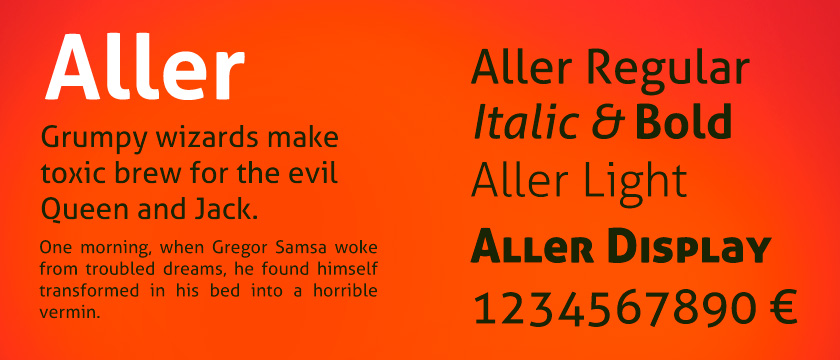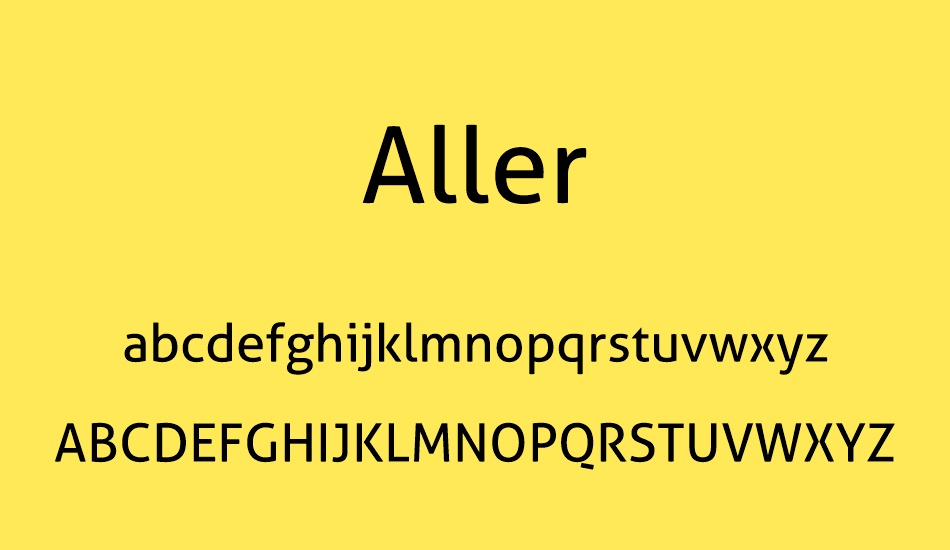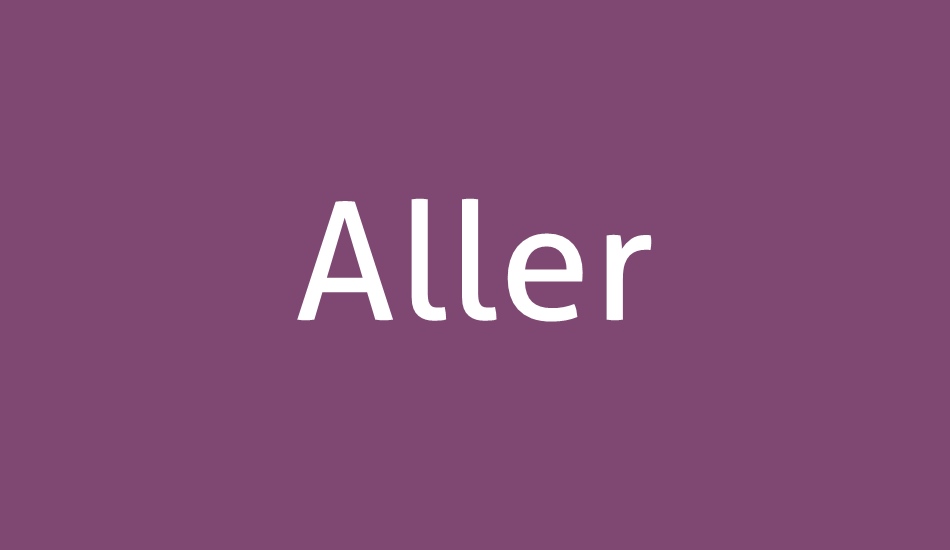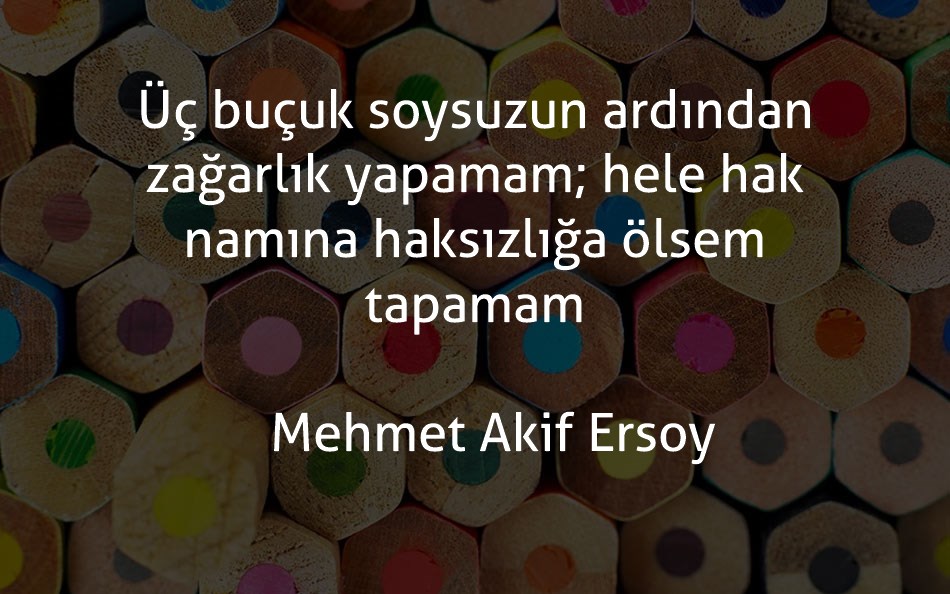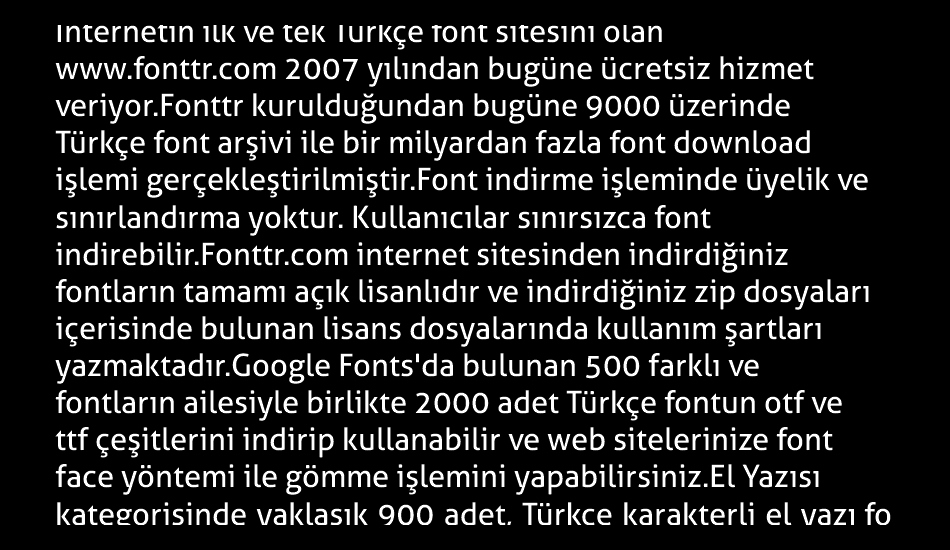
Aller font ailesi, 2008'de Danimarka Medya ve Gazetecilik Okulu için, yayıncının Aller'in sponsorluğuyla yaratılmıştır. Serbest bırakılmasından itibaren, her bir organizasyonda 25 kullanıcıya kadar DSMJ web sitesinden ücretsiz olarak herkesin yararlanması sağlandı. DSMJ dağılımı sona erdiğinde, Aller Standard Edition için Ücretsiz Lisans ile ilkeyi sürdürmekten mutluluk duyuyoruz.
Aller font